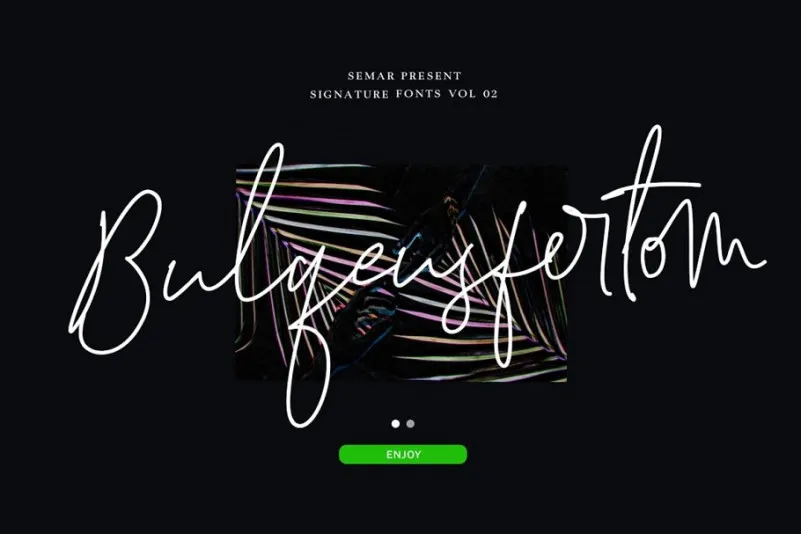
Bulqeusfertom - Signature Font
Olá! Este é Bulqeusfertom, uma nova fonte círula escrita à mão que destaca a essência natural da forma humana. Seu design original e autêntico reflete uma experiência de escrever com confiança e coragem, gerando um texto elegante perfeito para diversas aplicações. Perfeita tanto no formato regular quanto alternativo, Bulqeusfertom é uma fonte de assinatura que se destaca por sua beleza e simplicidade. Ideal tanto para logotipos e sites pessoais quanto para capas de catálogos ou capa de livros, ela também combina perfeitamente com aplicativos de mídia social como Instagram Stories e YouTube Thumbnails. Suas características círulas e elegantes tornam Bulqeusfertom uma opção versátil e impecável para qualquer projeto que exija um toque delicado e autêntico.